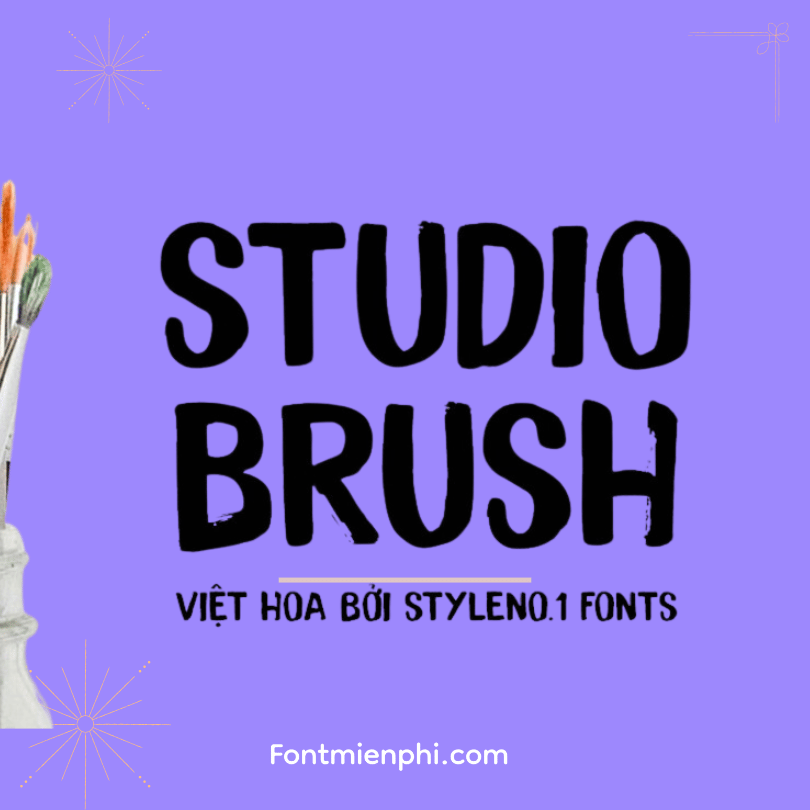
Việt hóa font SVN Studio Brush
Font Việt Hoá SVN Studio Brush – Nét Cọ Nghệ Thuật, Đậm Chất Sáng Tạo
Font SVN Studio Brush được Việt hóa với phong cách brush-hand (nét cọ mềm mại), mang lại cảm giác tự nhiên, phóng khoáng, phù hợp cho thiết kế poster, logo, bìa sách, và các dự án sáng tạo. Font hỗ trợ đầy đủ dấu tiếng Việt, giúp thiết kế trở nên sinh động và cá tính.